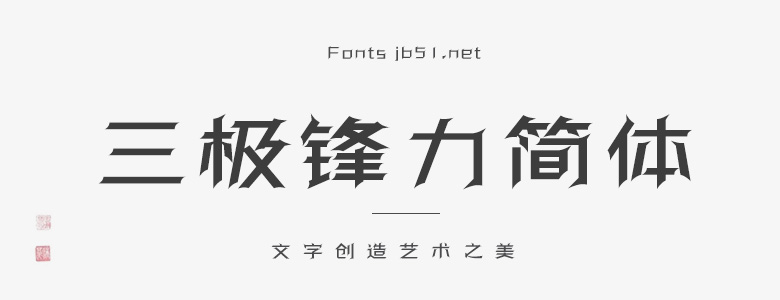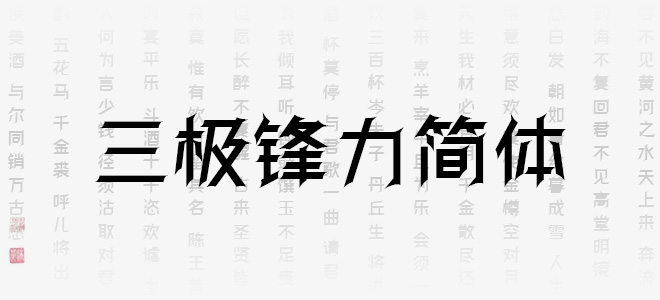
三極鋒力簡(jiǎn)體筆畫設(shè)計(jì)為直線、斜線等既有方向性又有力度的線形構(gòu)成的圖形,具有莊重、挺拔、有力等形式心里特征,能給人一種很強(qiáng)的理性和冷靜的視覺(jué)感受,適合表達(dá)某種特定的設(shè)計(jì)主題。創(chuàng)意卓越,個(gè)性突出。易于識(shí)別,便于應(yīng)用。歡迎喜歡三極鋒力簡(jiǎn)體的朋友前來(lái)下載使用。
三極鋒力簡(jiǎn)體